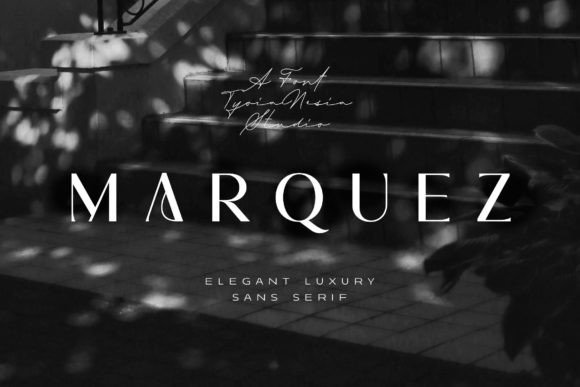
Marquez
適切なデザイン要素を見つけるのは難しい場合がありますが、Marquezは作品を即座に引き立てる優れたコレクションを提供します。
精密に作られたMarquezは、クリーンなベクター、滑らかなタイポグラフィ、そして安心のための商用ライセンスを提供します。
POD(オンデマンド印刷)製品、結婚式の招待状、またはソーシャルメディアのグラフィックを作成している場合でも、Marquezは理想的です。